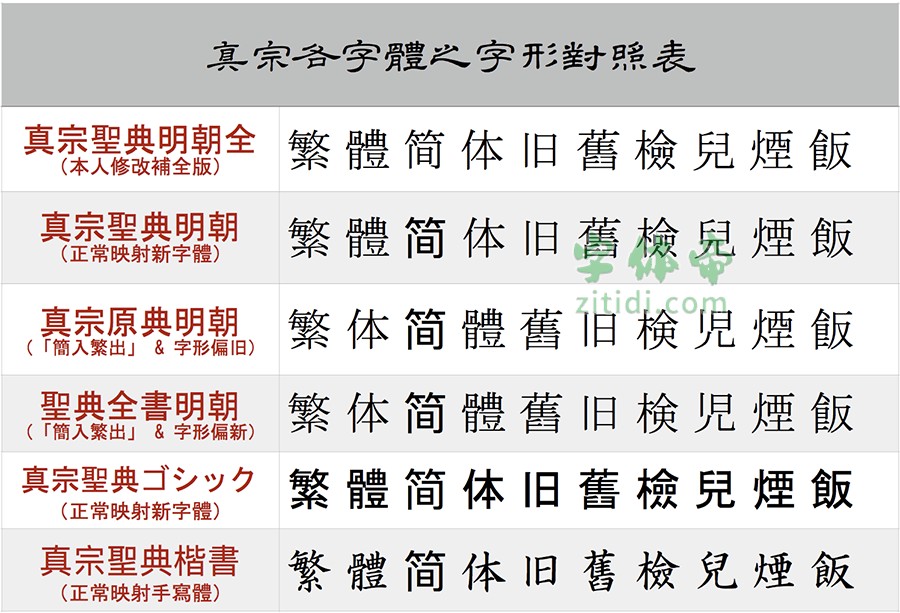
百度“旧字形吧”的吧主天王帝廷经常在网络上搜集各种传统的字形字体,偶然发现了日本的一个免费字体系列,就是这个“净土真宗圣典”系列字体。这个字体是为了将日本佛教「净土真宗派」的各大经典电子化而开发的字体,字体字形还原原书,颇具旧时铅字风韵。
然而应日本本地需求,字体采用了和大陆“简入繁出”字体一样的做法,输入日本的新字体则显示旧字体,输入原来的旧字体的话反而会显示新字体,完全无法满足中文地区的使用要求。虽然其中一个映射正常的“真宗圣典明朝”,然后而字形不如其它几个交换映射的字体“旧”,所以和一般的日本明朝体没什么差别。
于是天王帝廷以映射正确的真宗圣典明朝为本,用《原典明朝》和《全书明朝》的旧字形部分一一替换了真宗圣典明体中不够“旧”的部分,并用“思源明体细”来补充其简体和另外的一些缺字部分,形成了一套映射正确且字形够旧并而字库完整的字体——“真宗圣典明朝 全”。
天王帝廷所做的修改仅限于各个字体原有新旧字形的互换,和少数几个字形的修正,并未对此字体进行大规模的“旧字形化”修改,而且根据个人喜好保留了一些日本新字形特征,如“偏”、“所”等字。
本字体适合小号正文字体排版,且由于简体部分是思源明体补充的,在低分辨率设备上显示效果并不好,手机显示会显得笔划特别细,唯有在苹果电脑上显示效果尚可,我作为浏览器字体使用了很久,用来打印也不错。